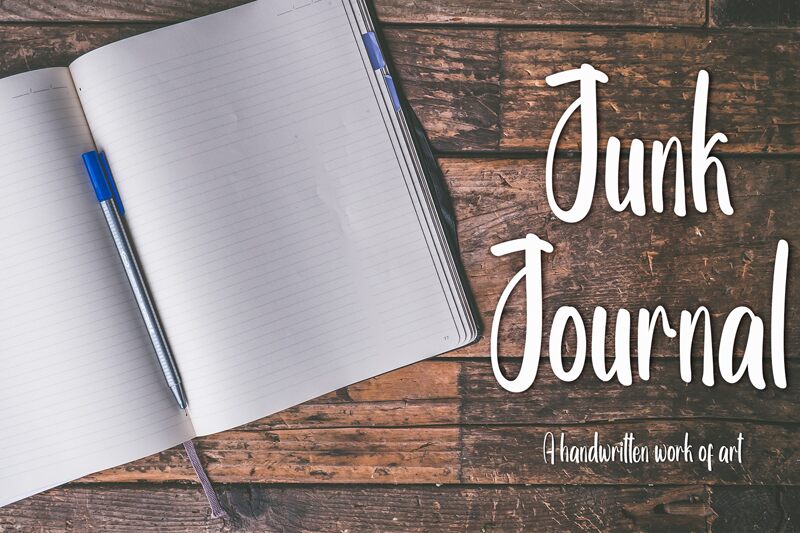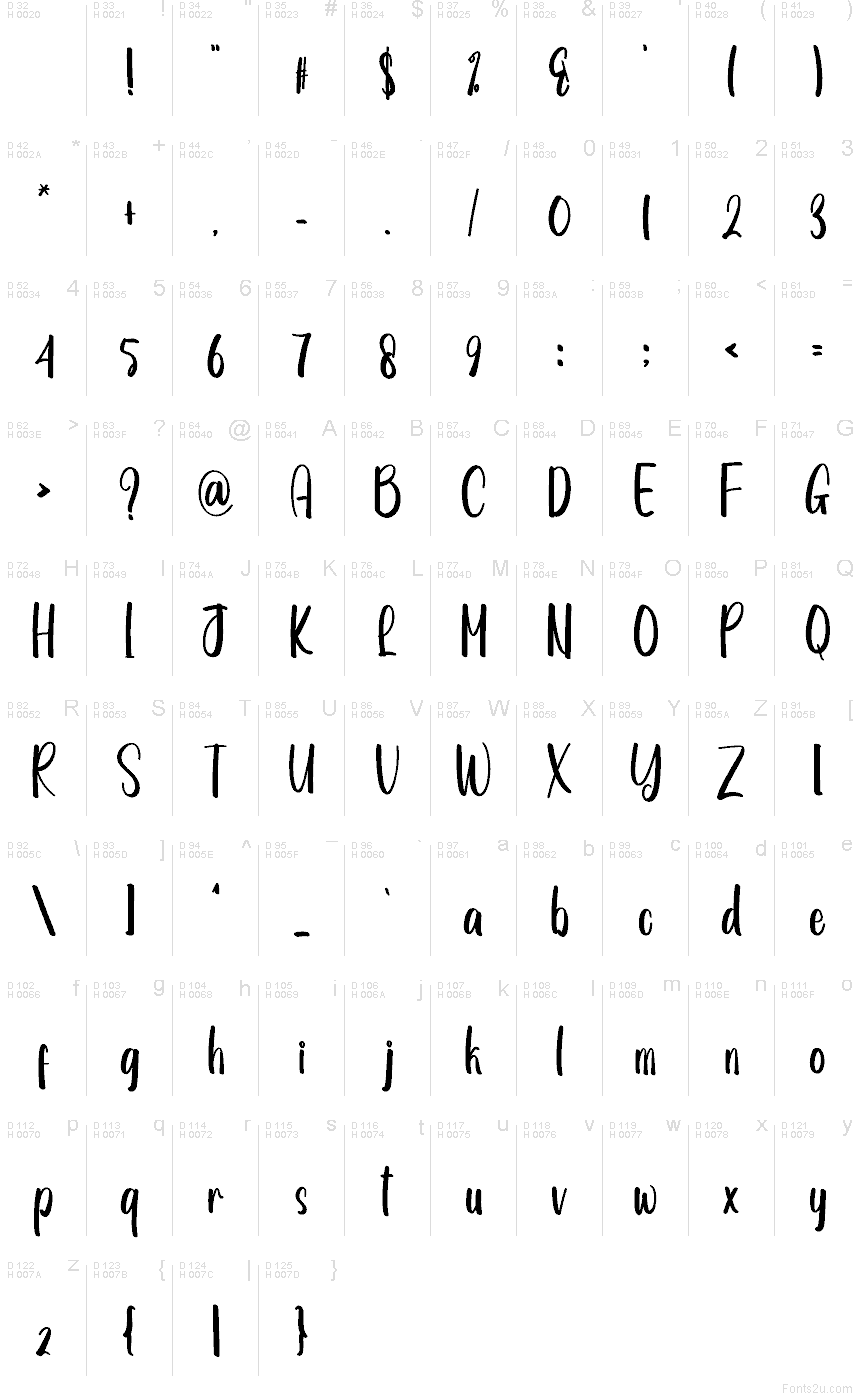
Junk Journal
Junk Journal — это бесплатный рукописный шрифт с высокими петляющими буквами «J» и расслабленным ритмом, напоминающим записи в личном дневнике. Буквы выглядят непринужденно и по-домашнему, а длинные вертикальные штрихи и скругленные соединения делают текст живым, словно это быстрая заметка, набросанная маркером.
Он отлично подойдет для заголовков в альбомах, дневникового брендинга, крафтовой упаковки, обложек книг и постов в соцсетях, где нужен бесплатный шрифт с «человеческим» и неформальным характером. Поскольку прописные буквы довольно высокие, а строчные остаются мягкими и простыми, шрифт хорошо смотрится в коротких заголовках, названиях на этикетках и разделах, где хочется передать ощущение ручной работы без лишней вычурности.